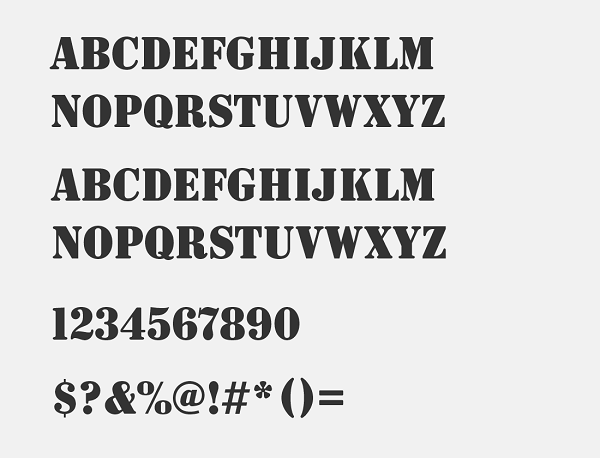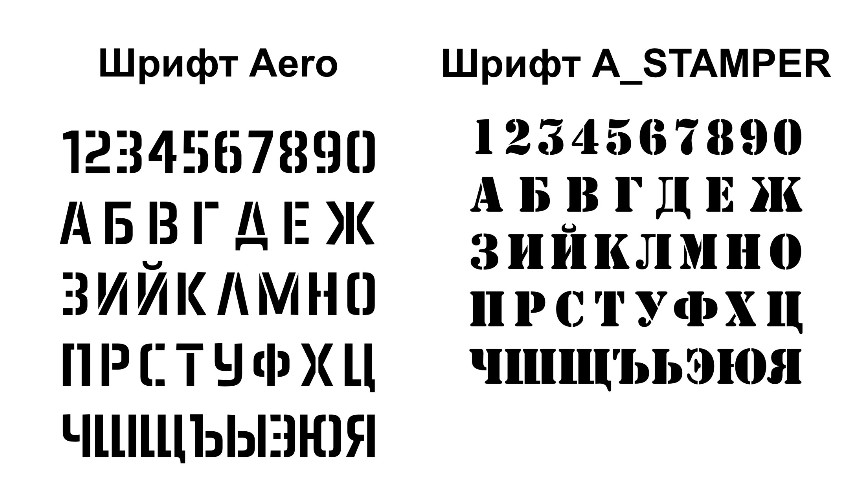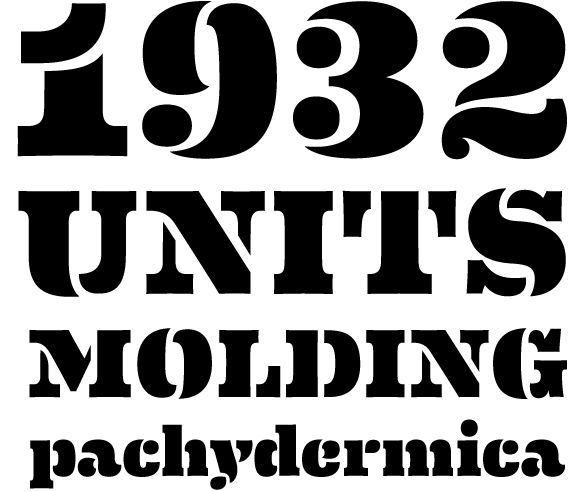
Шрифт трафарет: Трафаретные шрифты — каталог бесплатных шрифтов, которые Вы можете скачать
Лучшие трафаретные шрифты для дизайнеров (бесплатно и премиум)
Трафаретные шрифты, которые вы найдете ниже, варьируются от жирных (Black Ops One) до тонких (Stela UT), минимальных (College) и декоративных букв (Belladona Stencil).
Бесплатные трафаретные шрифты
Venture Time — трафаретный шрифт
Слисты — Странный шрифт трафарета